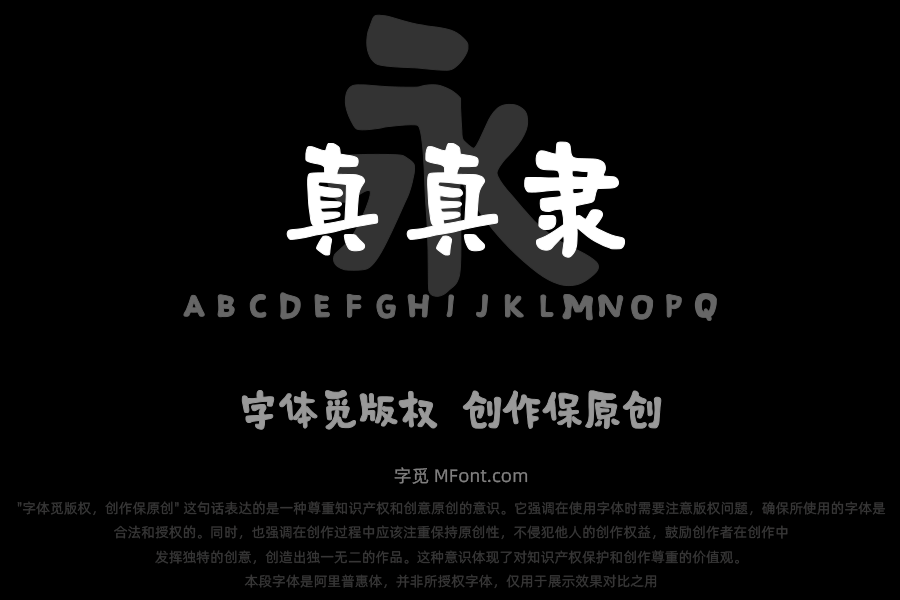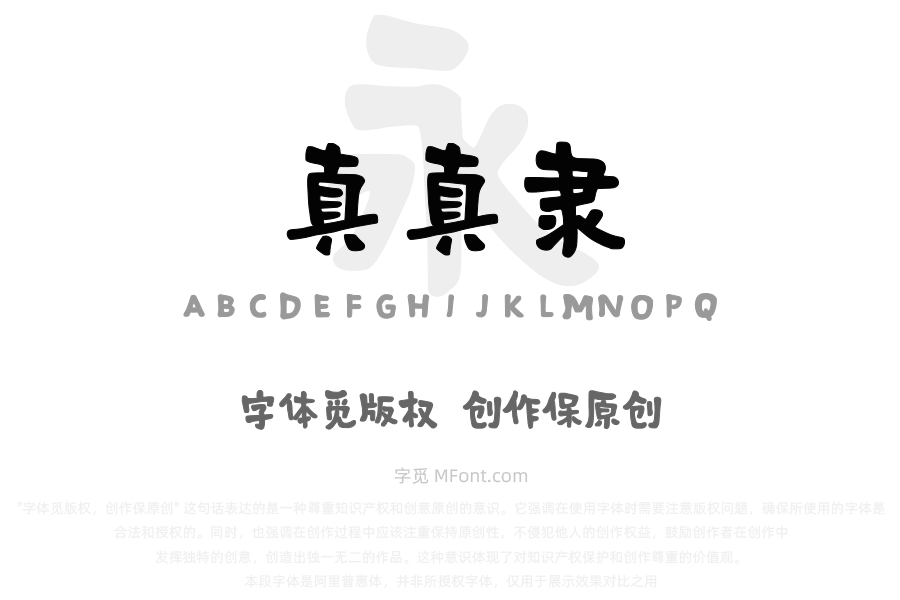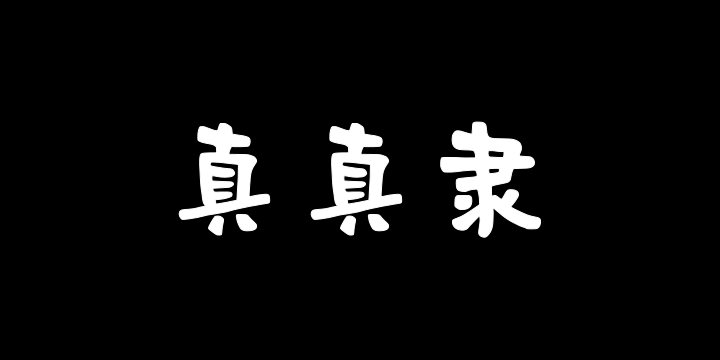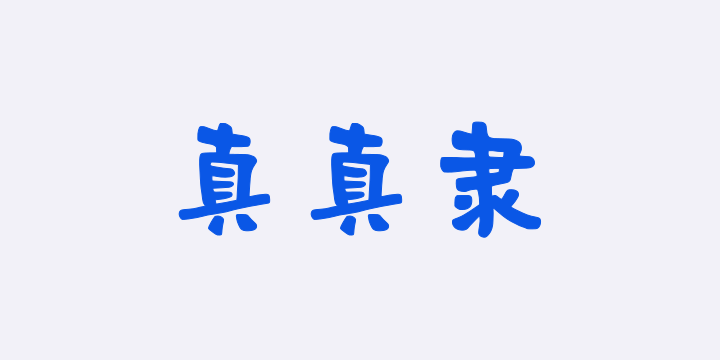
字潮真真隶
字潮字库
关于字潮真真隶字体字库信息
字体全名: 字潮真真隶
铸字厂: 字潮字库
设计师: 丁道华
字体简介: 字潮真真隶汲取传统书法的神韵,以现代设计语言重新诠释,呈现出刚柔并济的独特美感。其笔画粗壮有力,彰显出沉稳大气的视觉张力,同时在起笔、转承、勾捺处融入了圆润流畅的处理,巧妙化解了粗笔划可能带来的笨重感,赋予字形灵动的呼吸感。